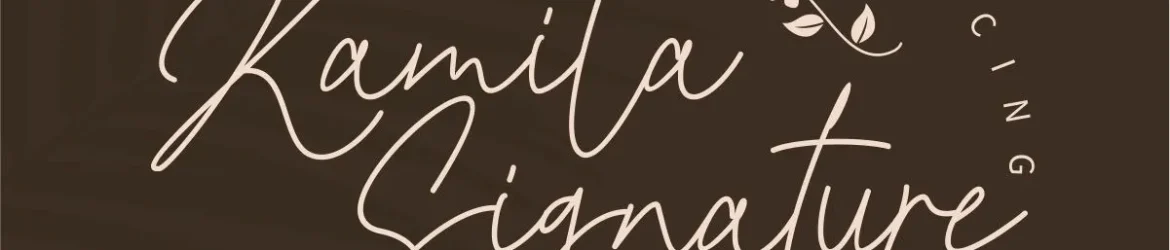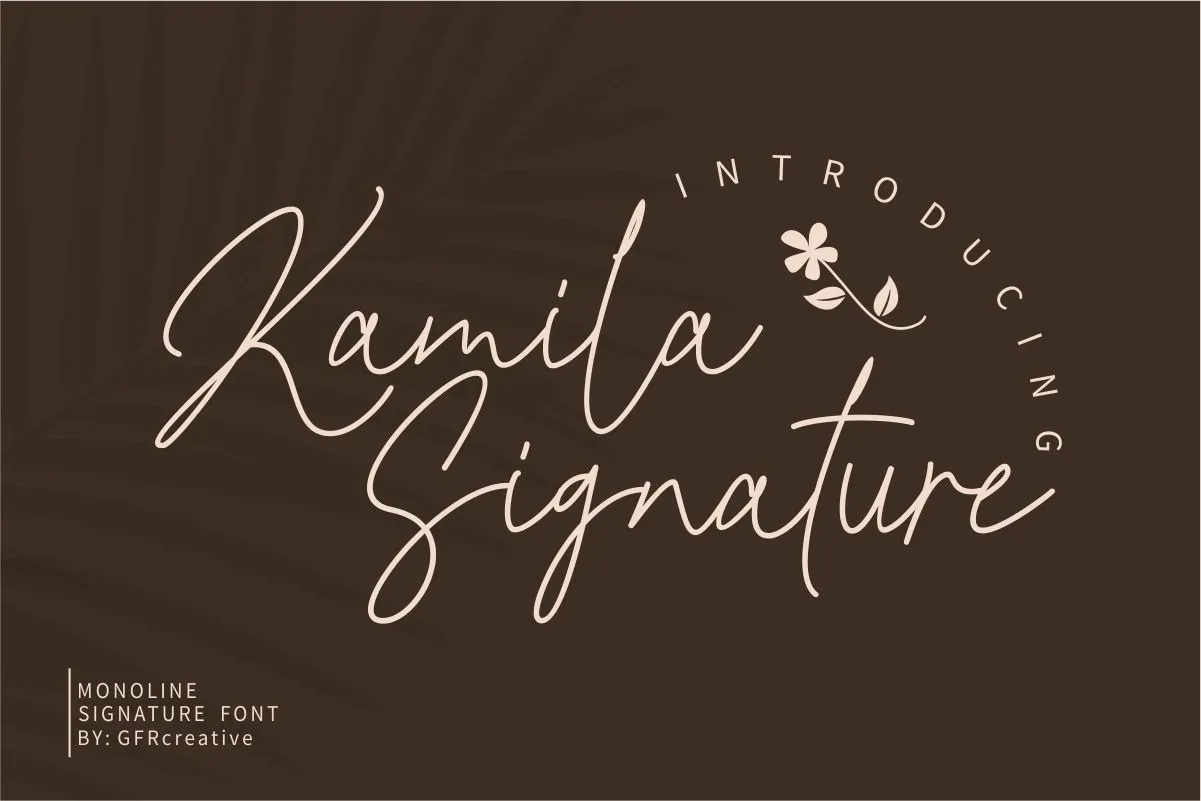
Kamila Signature Font – Fonte Grátis
Kamila Signature Font
A Kamila Signature Font é uma criação cuidadosamente desenvolvida pelo designer GFRcreative para quem busca uma fonte autêntica e única que se destaca entre as demais. Esta fonte foi construída com precisão de pressão e textura de tinta, fornecendo um efeito natural e quase hiper-realista aos seus projetos digitais. Com seu desenho fluido e elegante, a Kamila é perfeita para adicionar personalidade e profundidade em qualquer projeto. Seja em um layout editorial ou um design gráfico, o brilho único dessa fonte certamente fará sua marca. Ideal para aquelas criações que exigem uma personalização única e uma autenticidade intrínseca, a Kamila Signature Font é definitivamente uma adição imperdível à sua coleção de recursos gráficos.